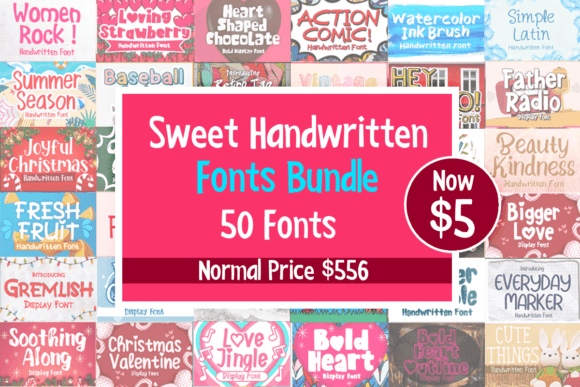
Sweet Handwritten Fonts Bundle
Việc tìm kiếm các thành phần thiết kế phù hợp có thể là một thách thức, nhưng Sweet Handwritten Fonts Bundle cung cấp một bộ sưu tập đặc biệt giúp nâng tầm công việc của bạn ngay lập tức.
Cho dù bạn đang tạo sản phẩm POD (In theo yêu cầu), thiệp mời đám cưới hay đồ họa mạng xã hội, Sweet Handwritten Fonts Bundle đều là một sự lựa chọn lý tưởng.